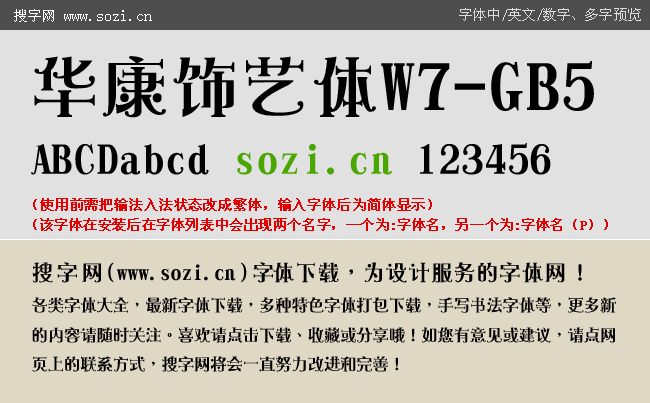
華康飾藝體W7-GB5
搜字網(wǎng)給大家提供一款帶有歐式風(fēng)格的華康飾藝體中文字體下載。華康飾藝體是一款帶有西方古典美的字體,橫細(xì)豎粗,起筆落筆處加有西方特色的櫬線裝飾,帶有一股濃濃的華麗復(fù)古感,字體造型復(fù)古、優(yōu)美又活潑,跟西方的花體字很類似。經(jīng)常被用于各種廣告、文案、標(biāo)題等方面。